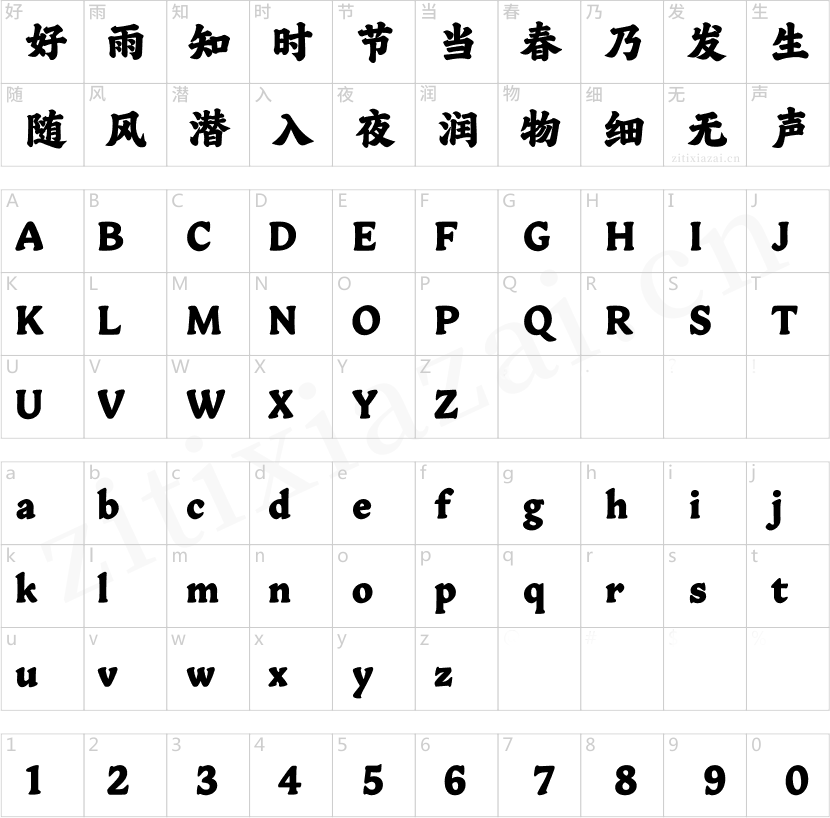
Aa老字号
Aa老字号,这款字体结构工整、笔画清晰,兼顾美观与易读性,适用于标题、正文、海报、包装、LOGO 等多种场景。字形优雅稳定,风格百搭耐看,适配日常排版与创意设计,让文字呈现更舒适、更具质感。Aa老字号一笔一画,皆是细节,以均衡的比例、流畅的线条打造舒适视觉体验,字形端正大气,风格简约现代。无论是商业设计、品牌宣传还是日常排版,都能轻松驾驭,让文字更有格调与力量。Aa老字号字体下载。
Aa老字号字体
Aa老字号是一款非常具有艺术性的字体,它的设计灵感来源于对古典艺术的研究,同时又融入了现代字体设计的元素。字形优美,笔画粗细变化自然,给人以大气、典雅的感觉。Aa老字号是一款既传统又现代的字体,它的设计充满艺术感,美观大方,实用性也非常强。无论是对于设计师还是对于普通读者来说,都是一种非常不错的字体选择。Aa老字号适合用于具有艺术感的场合,比如海报、宣传单张、书籍封面等。由于其字形流畅且具有动态感,也适合用于大量的文本排版,如报纸、杂志等。